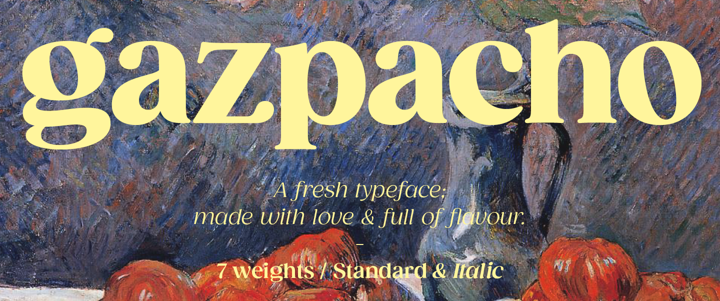
Gazpacho вдохновлен шрифтами с засечками, которые использовались в редакционных СМИ в 70-х и 80-х годах.
Морфология форм букв делает этот шрифт идеальным для таких целей, как логотипы и большие, смелые заголовки. Кроме того, благодаря большой высоте x-height он отлично подходит для заголовков с жестким лидированием. С другой стороны, высокий контраст и очень простые и узнаваемые формы делают его хорошо читаемым, поэтому он подходит и для небольших длинных текстов.